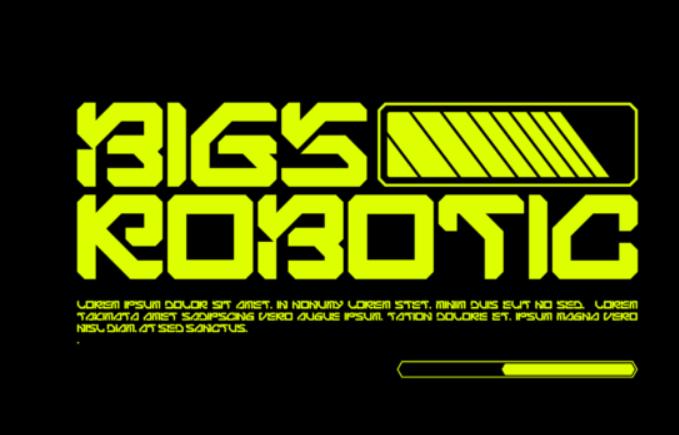
Bigs robotic - футуристический дисплейный шрифт в роботизированном стиле. Он отличается геометрическими формами, прямыми линиями и зигзагами, что придает ему современный и очень крутой вид!